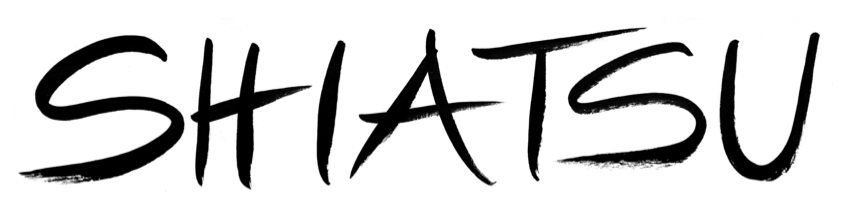
Pinselschrift (?) gesucht …
Der Schriftzug wurde vor ca. 10 Jahren für eine Messe verwendet, in ca. 2 m Breite. Wurde damals sehr scharf wiedergegeben, ich vermute daher dass das Vektordaten waren, eventuell aus einer Pinselschrift erstellt. Kennt die jemand? Oder eine sehr ähnliche – asiatisch angehaucht?